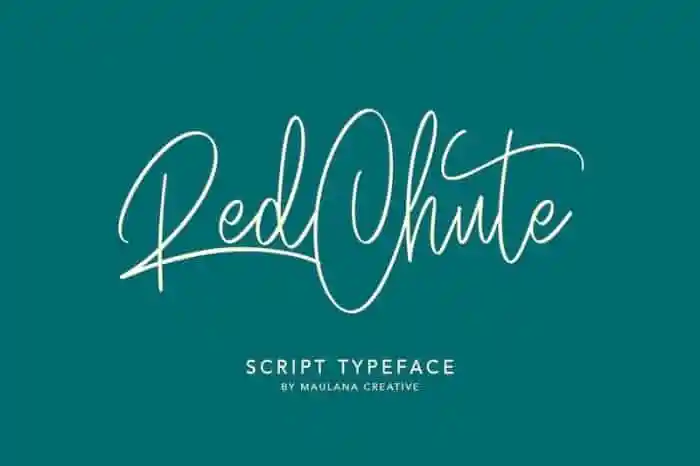
Red Chute Handwritten Font – Fonte Grátis
Red Chute Handwritten Font
A ‘Red Chute Handwritten Font’ é uma criação moderna do estilo script que traz aos designers uma escrita autêntica e elegante. Composta com a ferramenta de tinta-pen, ela foi projetada pelo designer Maulana Creative para um aspecto perfeito da escrita manuscrita real. Este recurso gráfico oferece uma opção única ao incluir um versão com desvio, onde as letras não estão tão próximas umas das outras. Isso faz a fonte se destacar ainda mais, proporcionando um visual ainda mais bonito e vívido. Ideal para aqueles que buscam adicionar uma pitada de sofisticação aos seus projetos, seja em editoriais de revistas, camisetas customizadas ou até mesmo em aplicativos móveis.